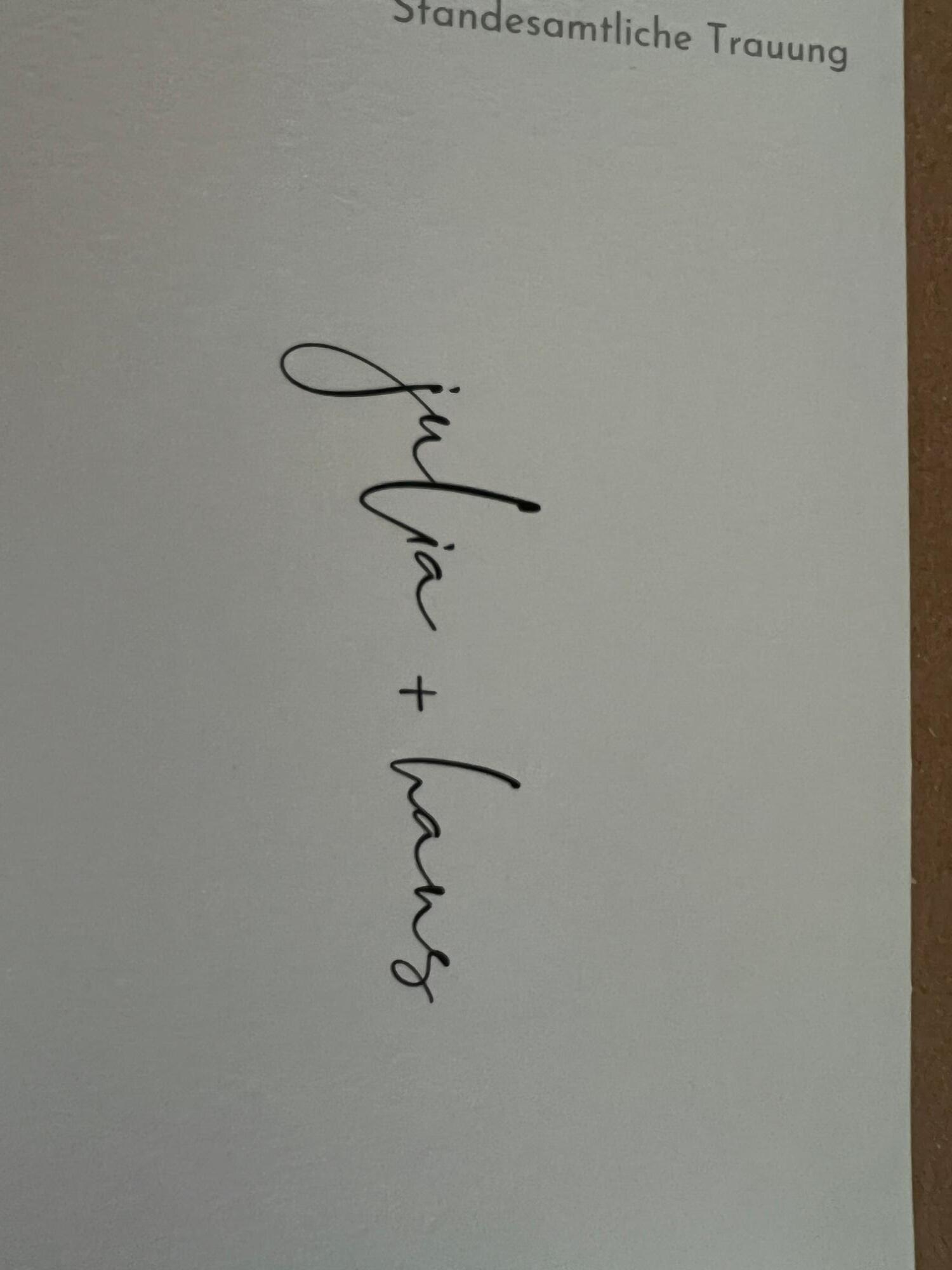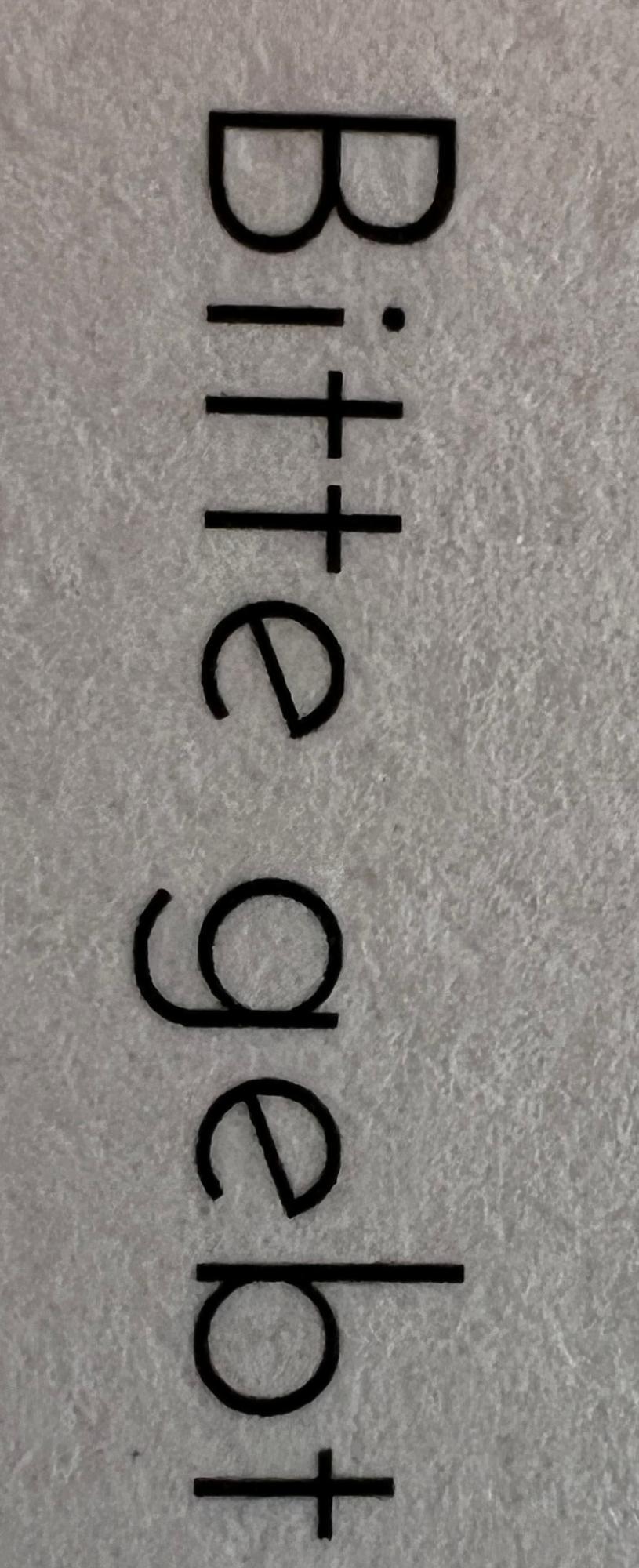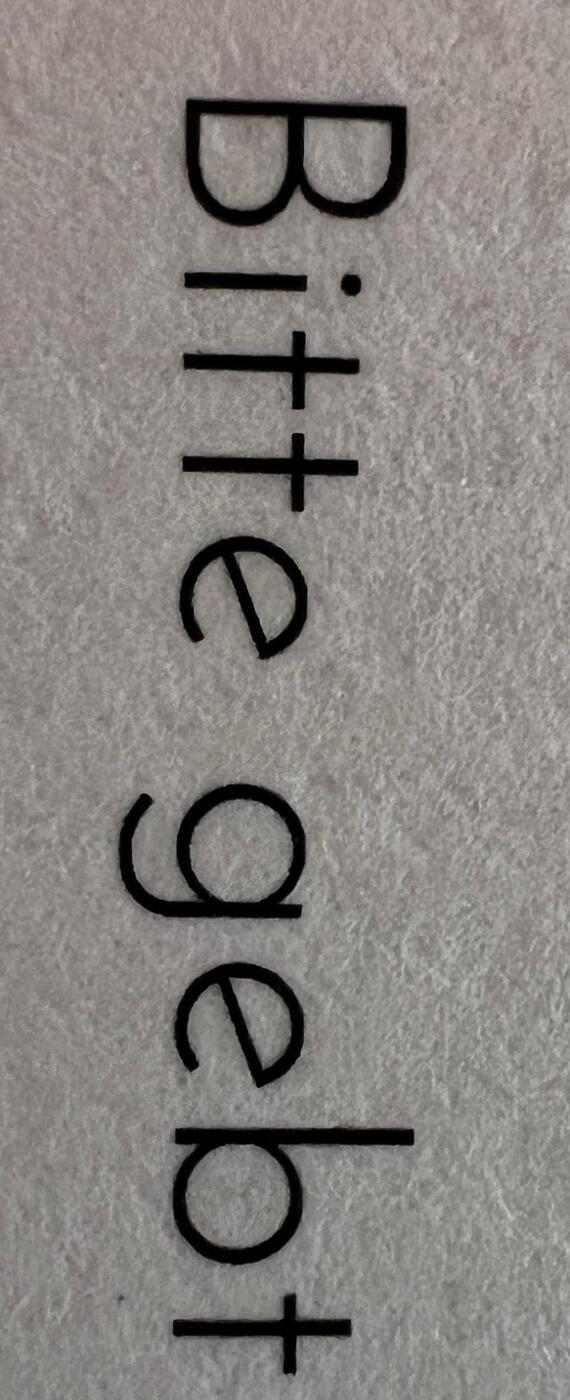
Suche diese Schriftart von einer aktuellen Einladungskarte und würde diese gerne für die Glückwunschkarte verwenden
ich würde mich wirklich sehr freuen, wenn ich herausfinden könnte, wie diese Schriftart heißt. Sie stammt von der Einladungskarte meines Neffen Hans und seiner Julia zur Hochzeit.
Ich habe schon alle möglichen Onlineportale wie what the font durchsucht und bin nicht fündig geworden.
Ich hoffe, ihr findet das ok, wenn ich noch nach einer weiteren Schrift frage. Auf der gleichen Einladung gibt es noch diese Schrift. Ich dachte, das wäre ganz einfach herauszufinden. Ich habe keine einzige Schriftart mit diesem Schrägstrich im e. Habt ihr eine Idee dazu?